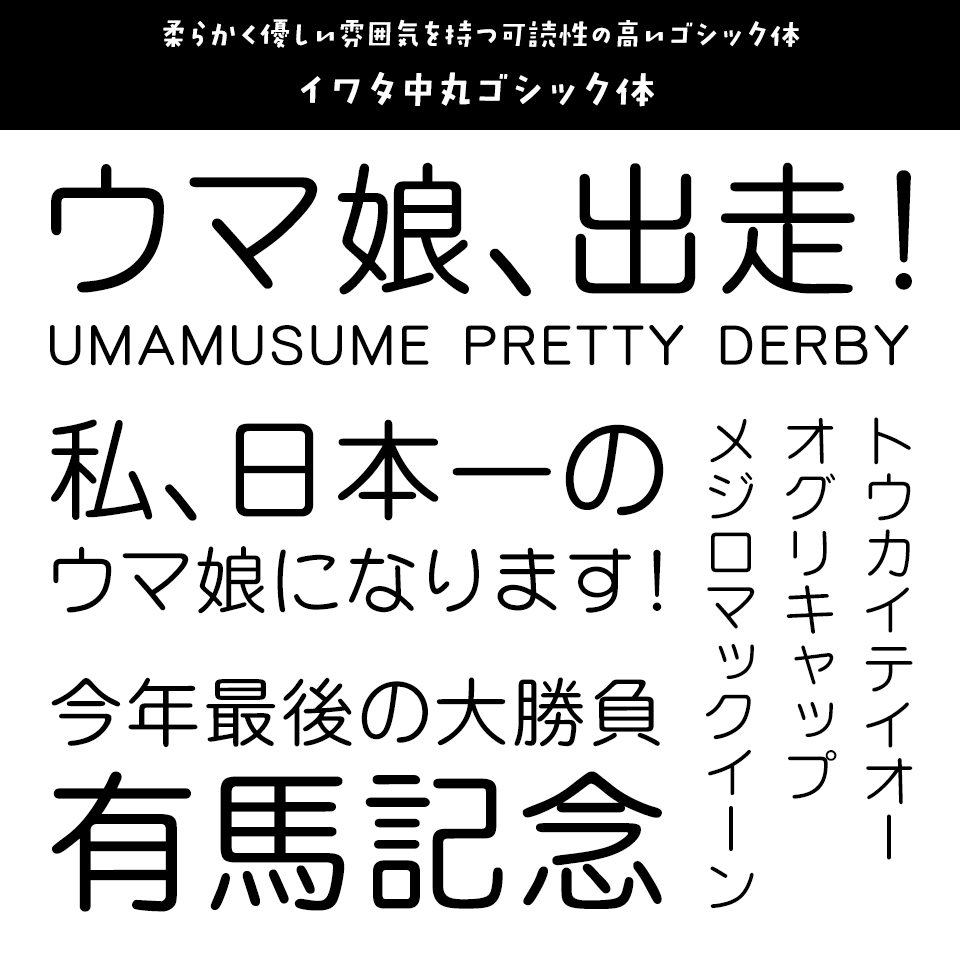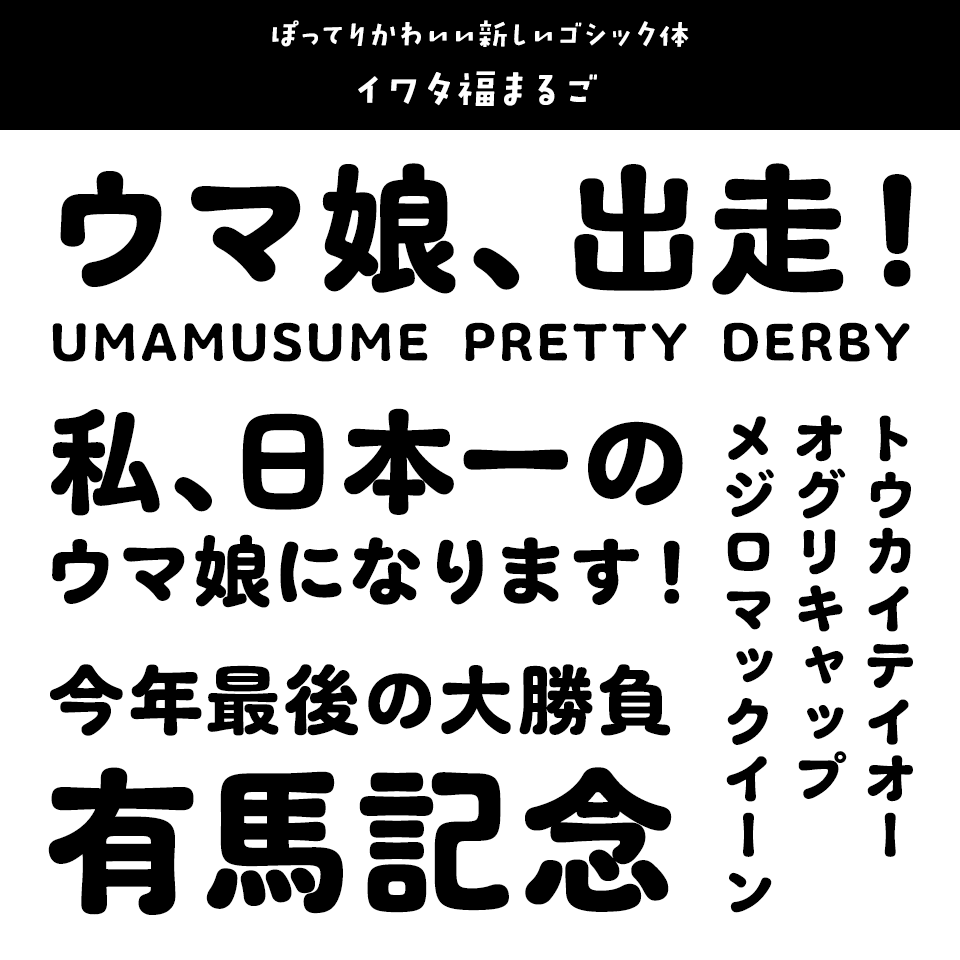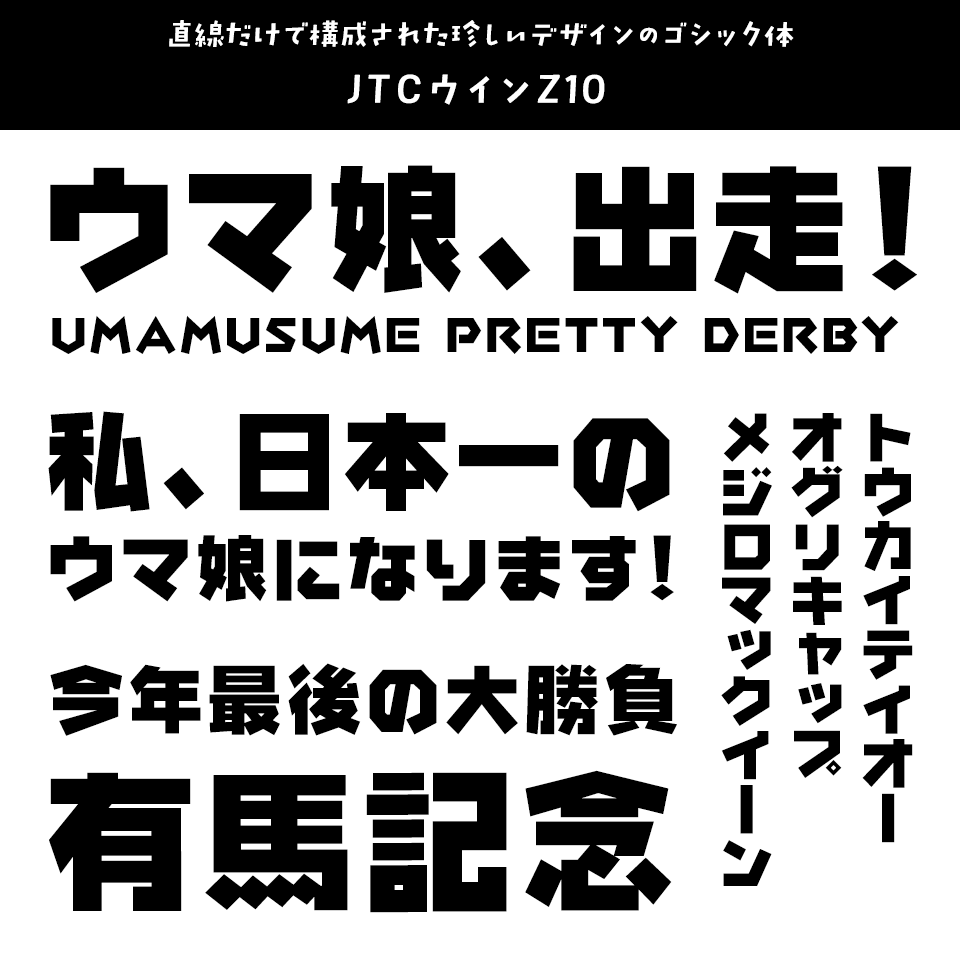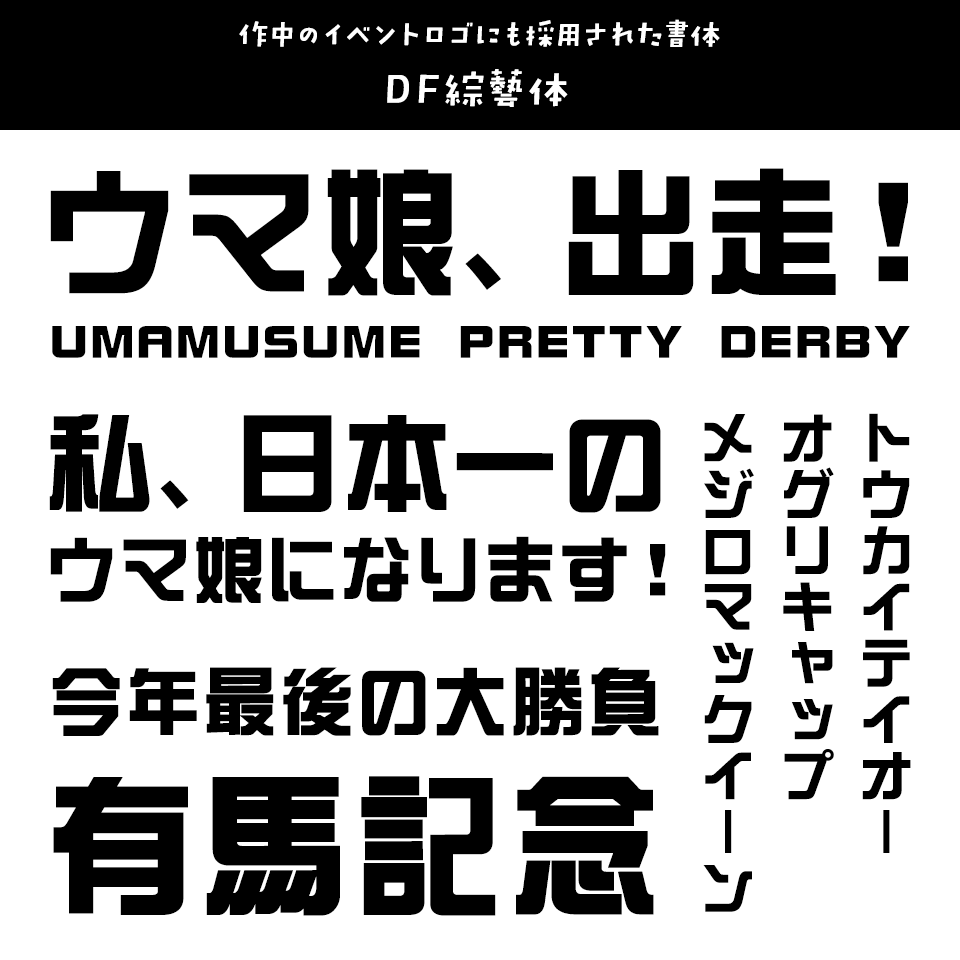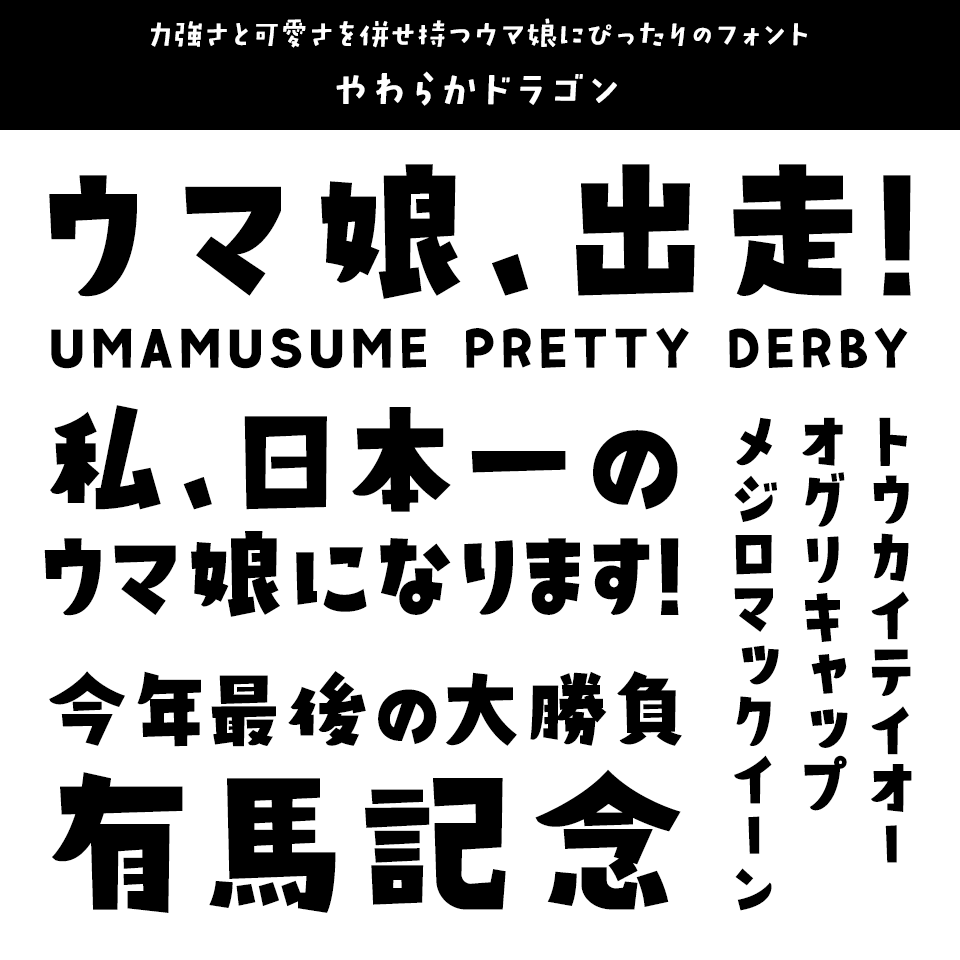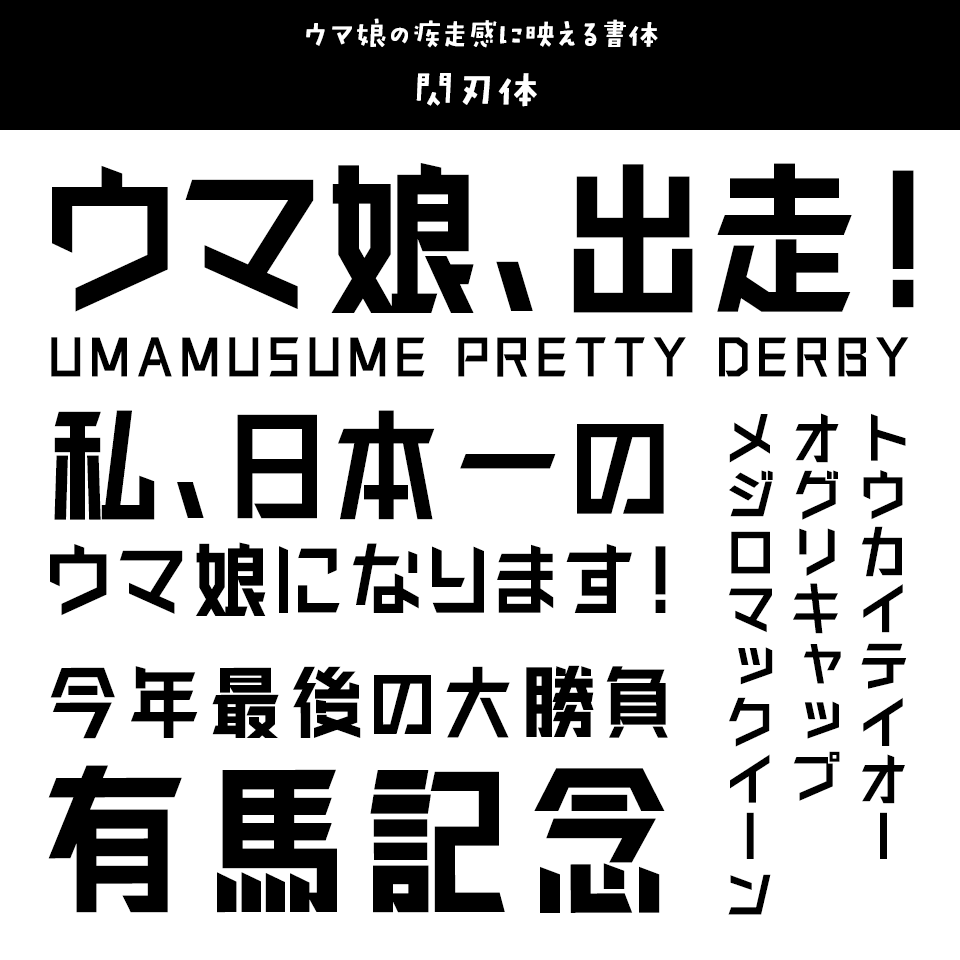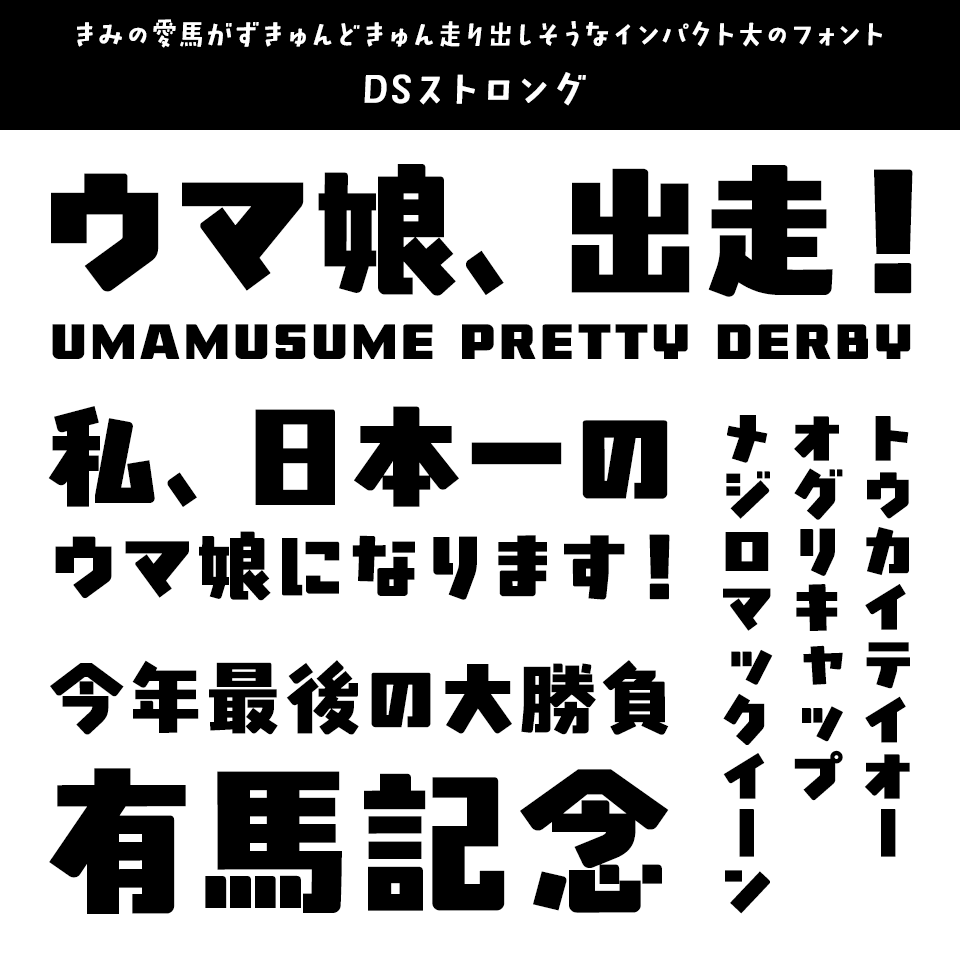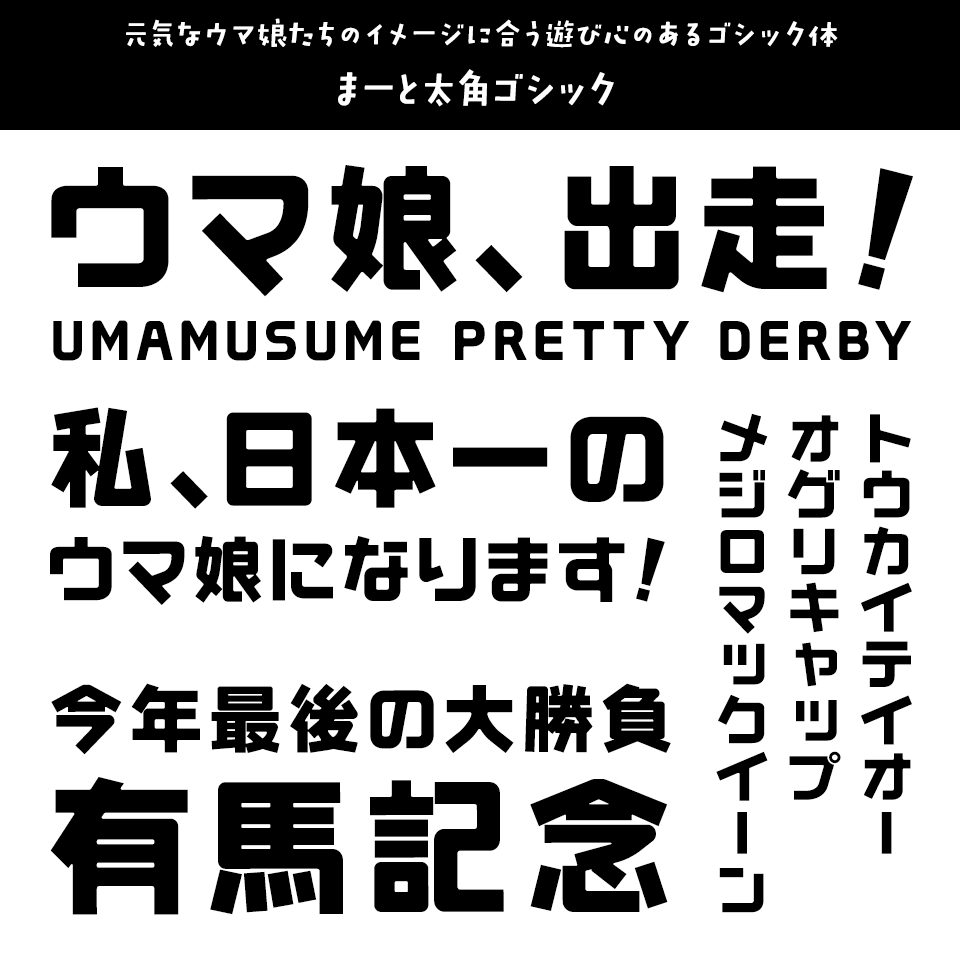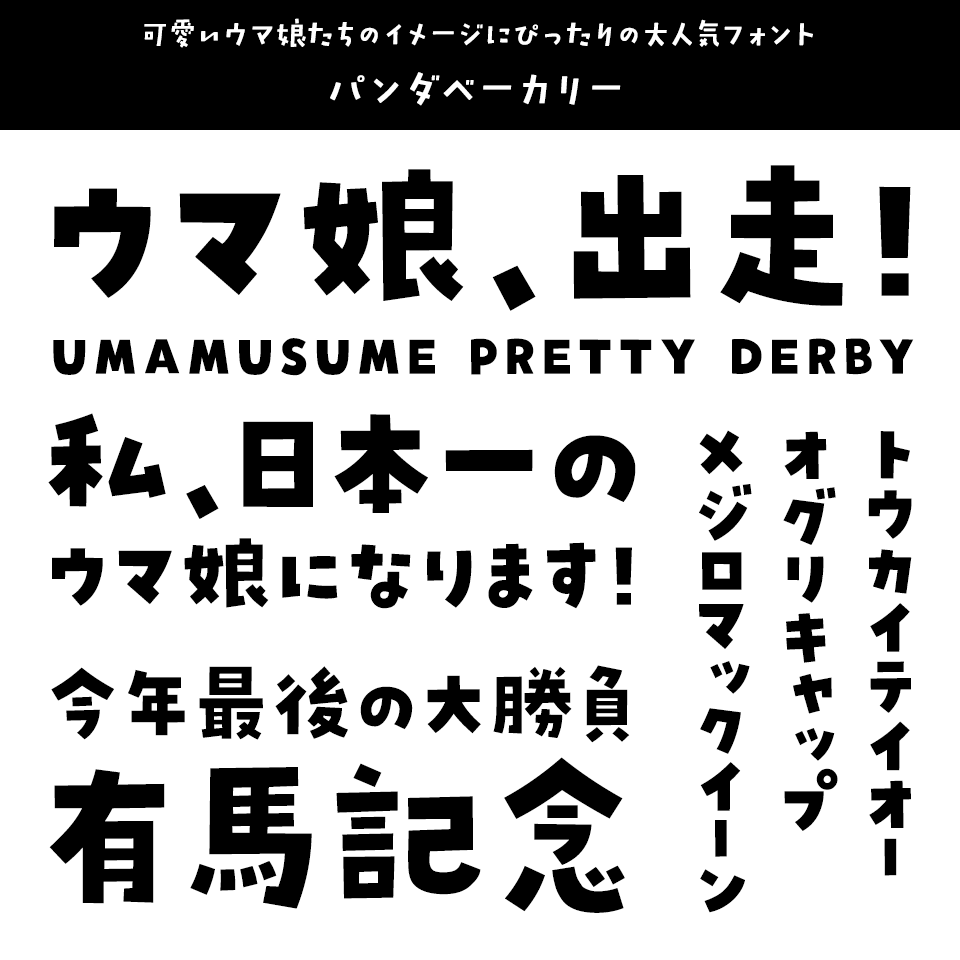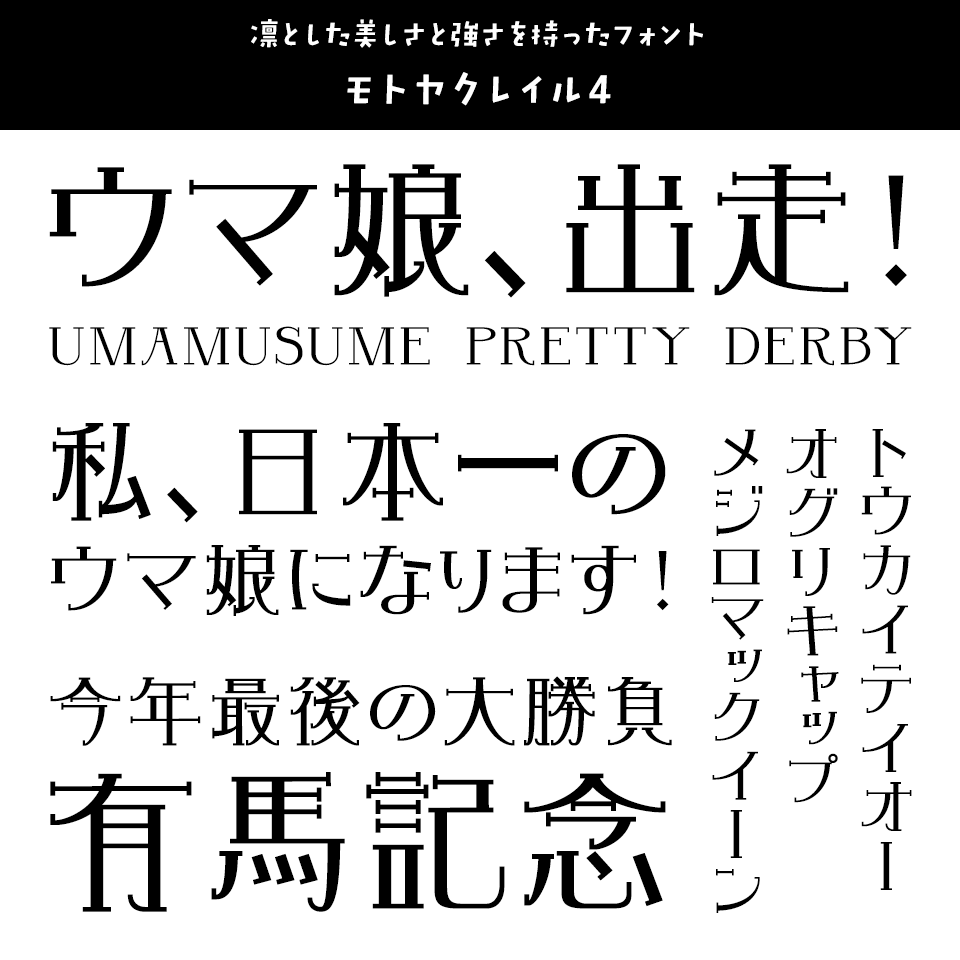
「ウマ娘」に合うフォント:特化型 目的別フォントガイド #177
今回は「ウマ娘」に合うフォント。日々フォントのことばかり考えている当店スタッフが直感的に選んだフォントをご紹介します。
「ウマ娘」に合うフォントをスタッフが選びました
「ウマ娘」に合うフォント イワタ中丸ゴシック体
柔らかく優しい雰囲気を持つ可読性の高いゴシック体
「ウマ娘」に合うフォント イワタ中丸ゴシック体
フェルトペンの柔らかみと親しみやすさが同人誌にもおすすめのシンプルなゴシック体です。
「ウマ娘」に合うフォント イワタ福まるご
ぽってりかわいい新しいゴシック体
「ウマ娘」に合うフォント イワタ福まるご
ゴシック体ともポップ体とも言い切れない、もっちりぽってりとしたシルエットが新しい、見出しから文字組まで汎用性の高い書体です。
「ウマ娘」に合うフォント JTCウインZ10
直線だけで構成された珍しいデザインのゴシック体
「ウマ娘」に合うフォント JTCウインZ10
直線だけで構成された極めて珍しいデザインのゴシック体。JIS第1・第2水準の約7,000文字の全てが直線のみで構成されており、曲線部分は1文字もありません。真っ直ぐなウマ娘たちにぴったりなフォントです。
「ウマ娘」に合うフォント DF綜藝体
作中のイベントロゴにも採用された書体
「ウマ娘」に合うフォント DF綜藝体
文字のすき間や形を整え、線の端にカーブを加えることで、太くてポップな印象をもつデザイン書体です
「ウマ娘」に合うフォント やわらかドラゴン
力強さと可愛さを併せ持つウマ娘にぴったりのフォント
「ウマ娘」に合うフォント やわらかドラゴン
力強くもあり、どこか柔らかい。そんなイメージの日本語フォントです。インパクトを持たせたい時、優しい印象を持たせたい時に。色々な使い方を試してみてください!
「ウマ娘」に合うフォント 閃刃体
ウマ娘の疾走感に映える書体
「ウマ娘」に合うフォント 閃刃体
刃のように鋭く、力強い筆遣いが魅力の書体。勢いある骨格と現代的なバランスが、ウマ娘のスピード感や躍動感ある世界観にぴったりです。
「ウマ娘」に合うフォント DSストロング
きみの愛馬がずきゅんどきゅん走り出しそうなインパクト大のフォント
「ウマ娘」に合うフォント DSストロング
岩石のような堅さ、力強さの中にも優しさを感じる、太く元気な書体。きみの愛馬がずきゅんどきゅん走り出しそうな、インパクト大のデザインがウマ娘にぴったりです。
「ウマ娘」に合うフォント まーと太角ゴシック
元気なウマ娘たちのイメージに合う遊び心のあるゴシック体
「ウマ娘」に合うフォント まーと太角ゴシック
角ばった字形の太角ゴシック体のフォント。元気なウマ娘たちのイメージに合う、遊び心のあるデザインです。
「ウマ娘」に合うフォント パンダベーカリー
可愛いウマ娘たちのイメージにぴったりの大人気フォント
「ウマ娘」に合うフォント パンダベーカリー
手描きのような自然なリズム感と、見出しやパッケージにも最適なしっかりとした太さ。そして何より手作り感のある可愛らしさ。かわいいの新定番・大人気フォントです。
「ウマ娘」に合うフォント モトヤクレイル4
凛とした美しさと強さを持ったフォント
「ウマ娘」に合うフォント モトヤクレイル4
文章に「ツヤ」「光沢感」を付与できるデザイン書体です。その性質から、書体名にはフランス語で「明るい」「光」を意味する「Clair(クレイル)」と名付けました。制作時のこだわりのポイントとして、文字のハランスは全て足長気味にデザインし、あえて重心を高めに設定することで“「美」への意識の高さ”を表現してみました。
「ウマ娘」に合うフォント DF優雅宋 W7
ウマ娘の持つ優雅さや華やかさを表現できるデザインフォント
「ウマ娘」に合うフォント DF優雅宋 W7
細い横線と太い直線で構成され、ストロークの先端と末端に欧文書体の花文字のような装飾が施されているのが特徴的な書体です。この特徴が古典的な洋風感を引き出し、優雅さや華やかさを表現しています。
「ウマ娘」に合うフォント DFロマン雪
愛らしいウマ娘たちを表現したようなデザインフォント
「ウマ娘」に合うフォント DFロマン雪
大正14年の藤原太一著書による『図案化せる実用文字』から着想を得て、図中の婦人の華麗な装いや愛らしいスタイルをヒントにして、大正末期から昭和初期にかけての古典ロマンの雰囲気を再現した書体です。
「ウマ娘」に合うフォント DF麗雅宋 W9
華麗なウマ娘たちのウイニングライブの雰囲気に合うデザインフォント
「ウマ娘」に合うフォント DF麗雅宋 W9
明朝体のストロークをより美しく、そして特徴的にアレンジし、華麗な雰囲気を演出したロマン風書体。
「ウマ娘」に合うフォント あめちゃんポップ まる
ウマ娘の元気で親しみやすい世界観にフィットするフォント
「ウマ娘」に合うフォント あめちゃんポップ まる
まるをあちこちに散りばめた、ぽってりかわいいポップな太めのフォントです。応援うちわやアイドル風デザインにもぴったりです。
「ウマ娘」に合うフォント JTCじゃんけんU
ほがらか、楽しいウマ娘たちイメージに合うデザインフォント
「ウマ娘」に合うフォント JTCじゃんけんU
「じゃんけんU」はPOP書体とは少し違うかもしれませんが、遊び心が詰まった面白いデザインです。極太のウエイトは存在感があり、広告やくだけた記事の見出しなどに最適。
「ウマ娘」に合うフォント ユールカ
ウマ娘の作中でも度々使用される脱力系デザインフォント
「ウマ娘」に合うフォント ユールカ
遊び心のある脱力系のゆるい書体です。ひと文字がそれぞれ不安定かつユニークなデザインで、手描き風書体のもつ《あたたかい》《やさしい》《素朴》を表現するのに最適で、さらには極太ウエイトならではの《柔らか》《ほがらか》な表情をもつ書体です。
「ウマ娘」に合うフォント 闘龍書体
激しいウマ娘たちのレースにピッタリな力強い毛筆フォント
「ウマ娘」に合うフォント 闘龍書体
闘争心にあふれ、力がありあまった若い龍が、空を舞うさまをイメージして作られた筆書系デザイン書体です。
「ウマ娘」に合うフォント DFてがき速 W3
疾走感ある走り書きが、汗と青春の味
「ウマ娘」に合うフォント DFてがき速 W3
走り書きの手書き文字が疾走感を演出します。手書き文字だから、青春を駆け抜けるウマ娘たちのリアルを感じさせます。
「ウマ娘」に合うフォント やんちゃポップ じたばた